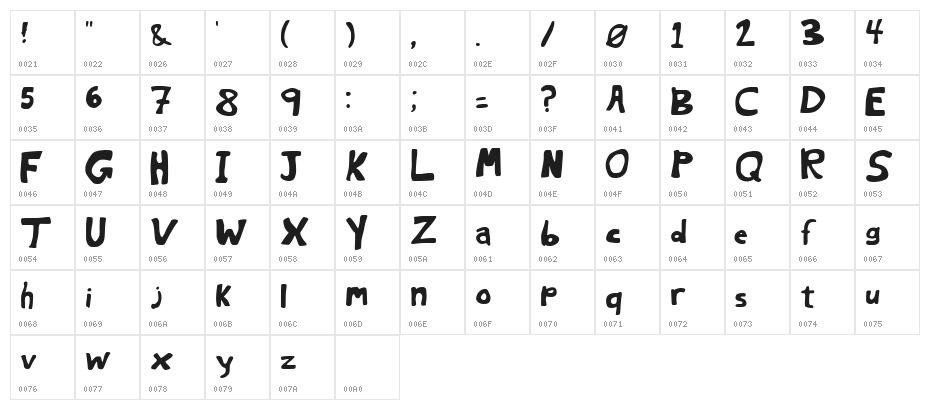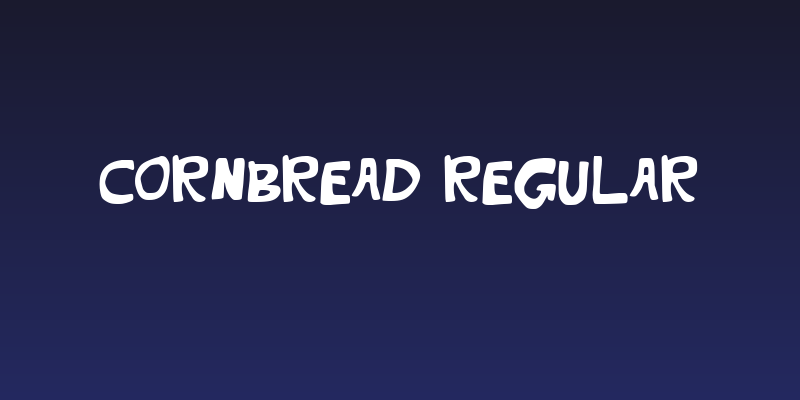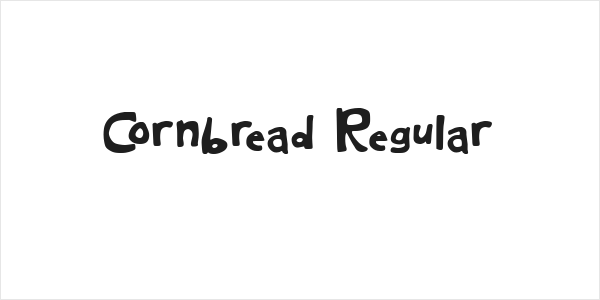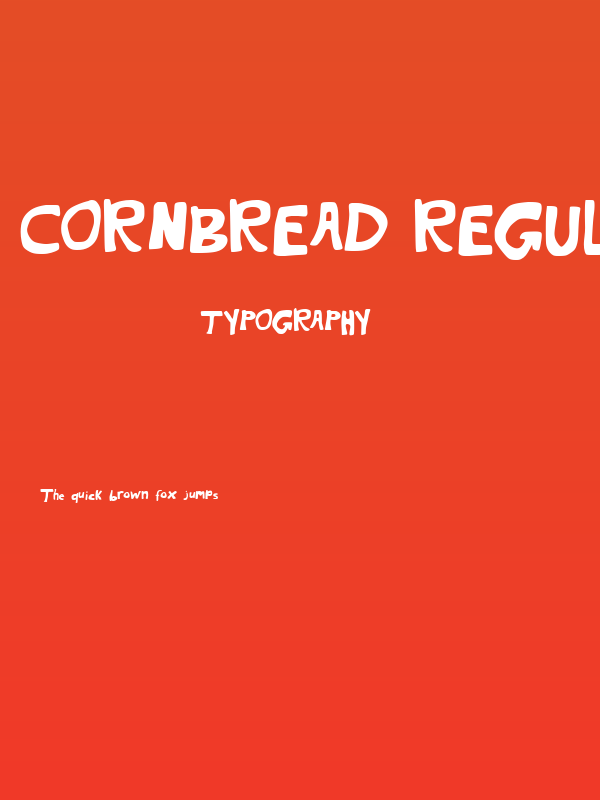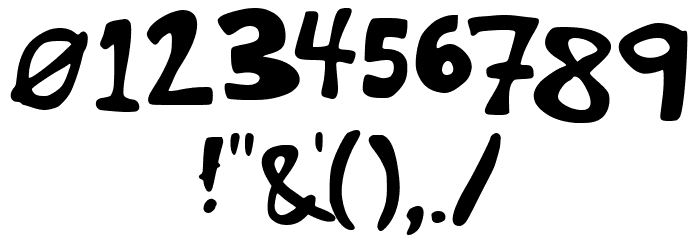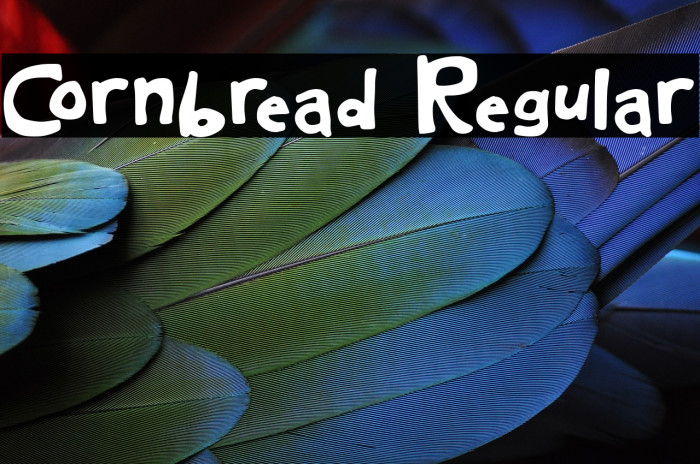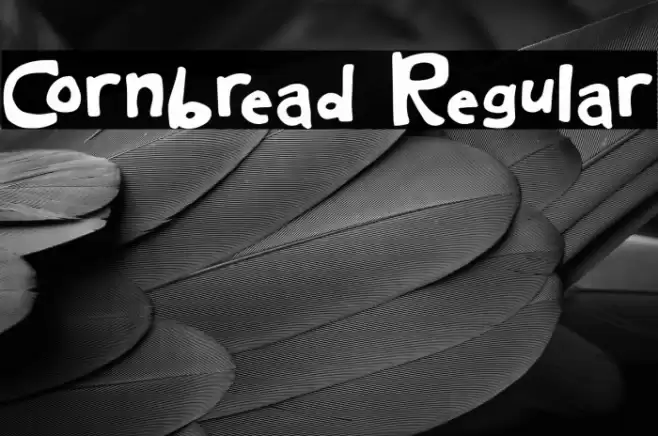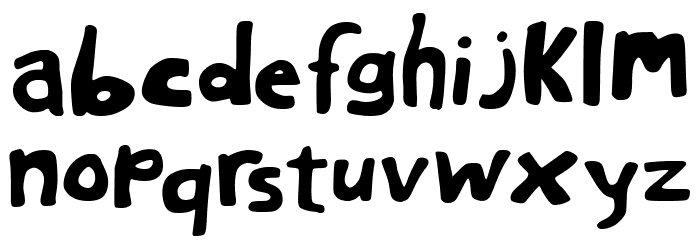
Cornbread Regular Font
| Familia fontului | Cornbread |
| Proiecte propuse | Ideal for children's books, playful branding, casual invitations, and creative posters. |